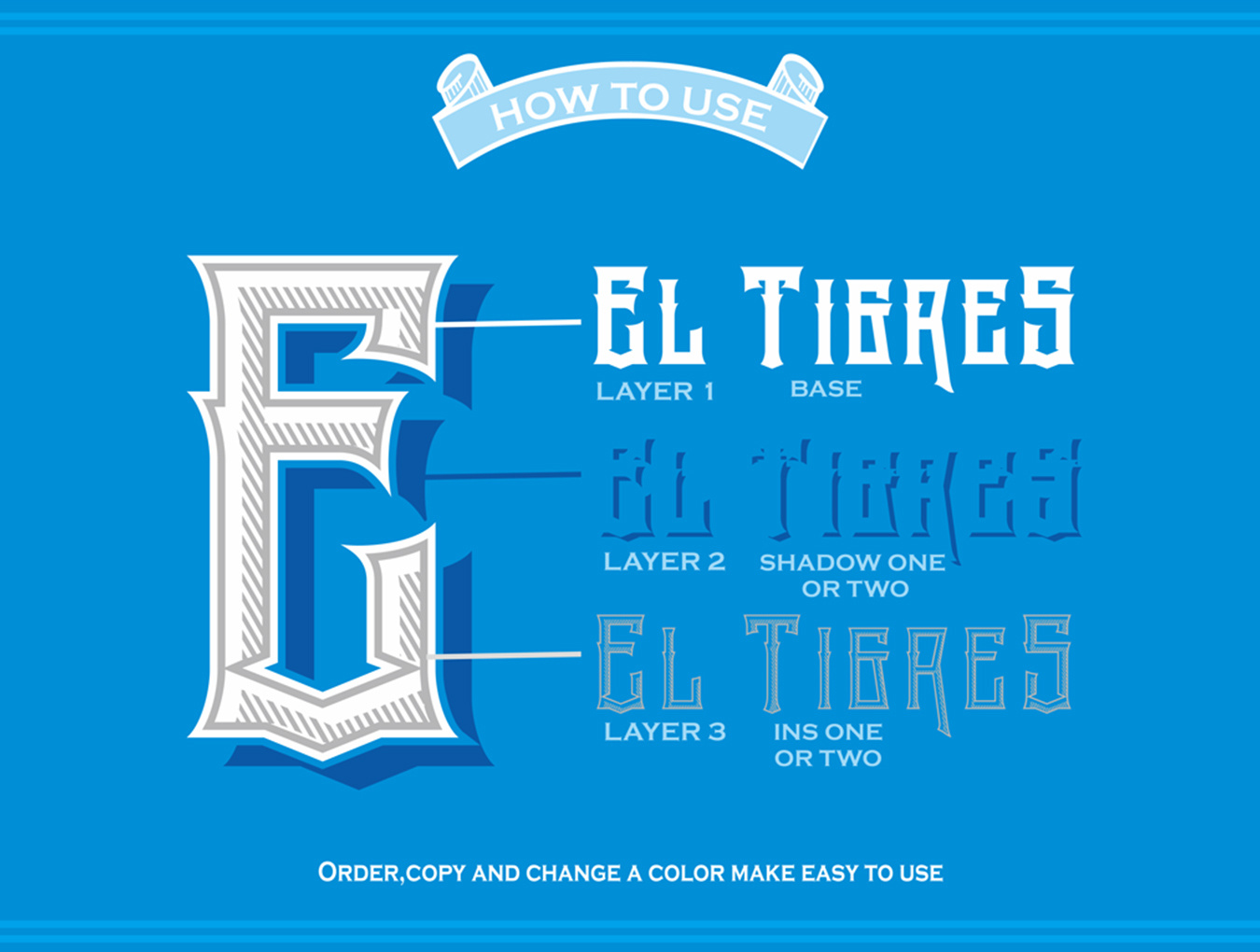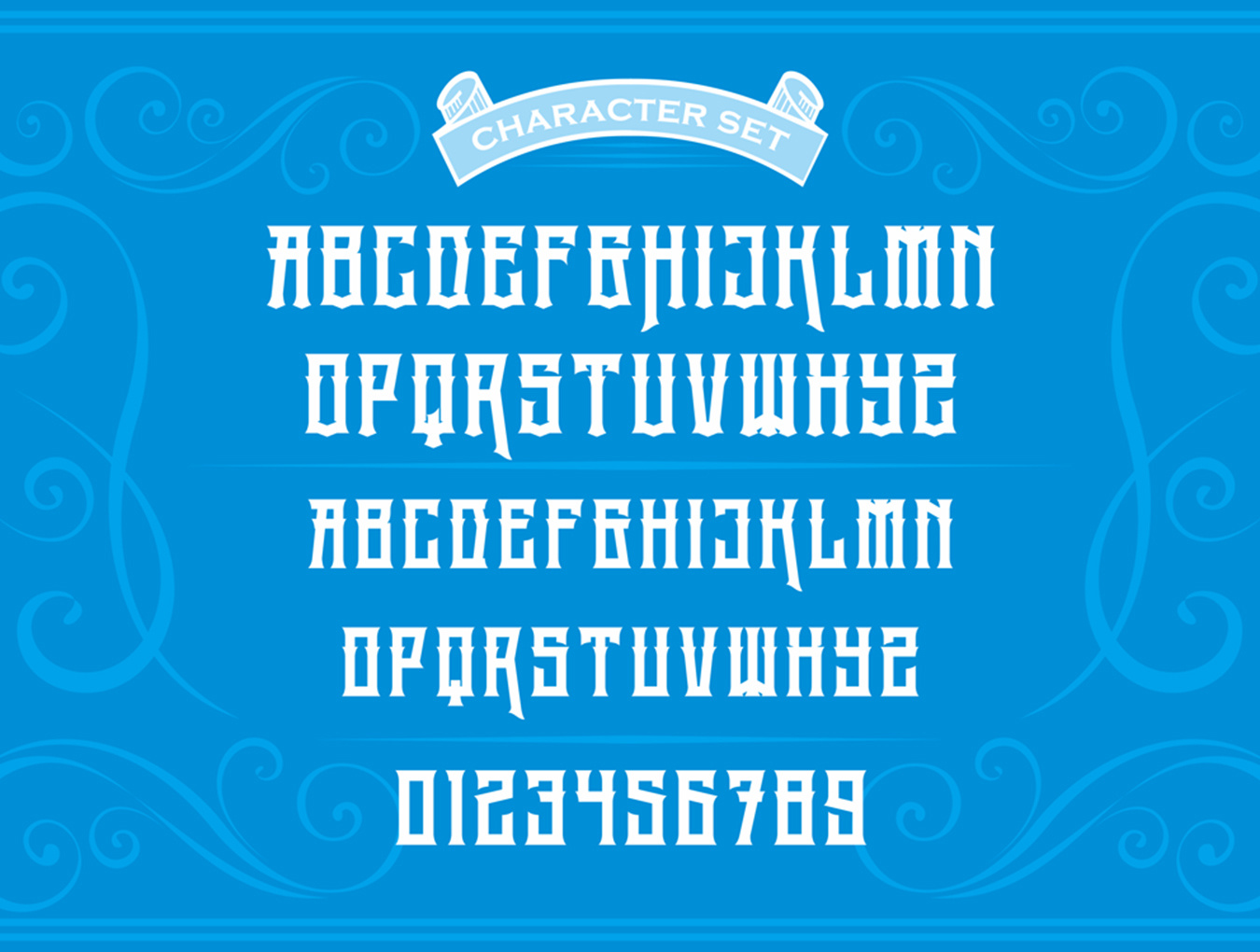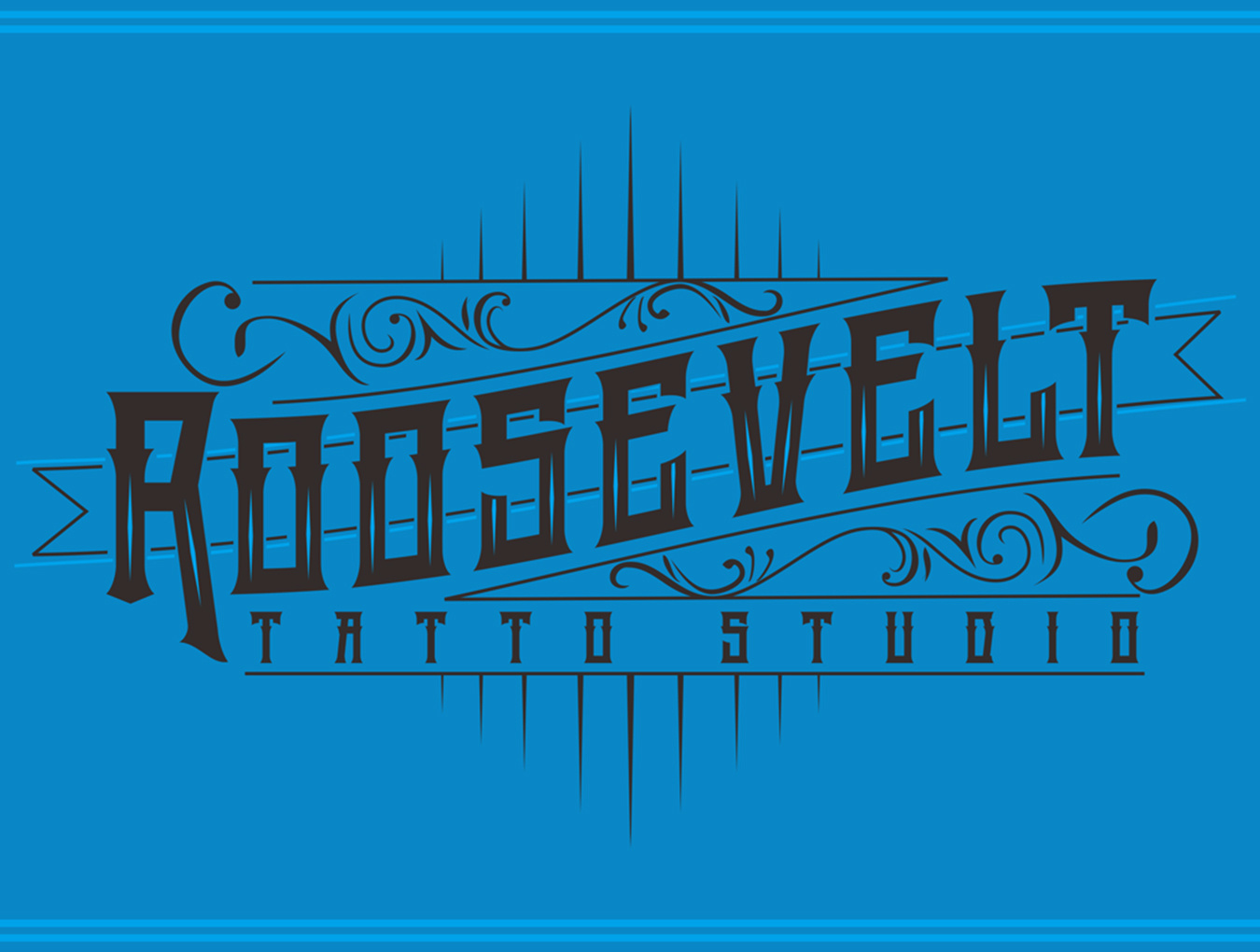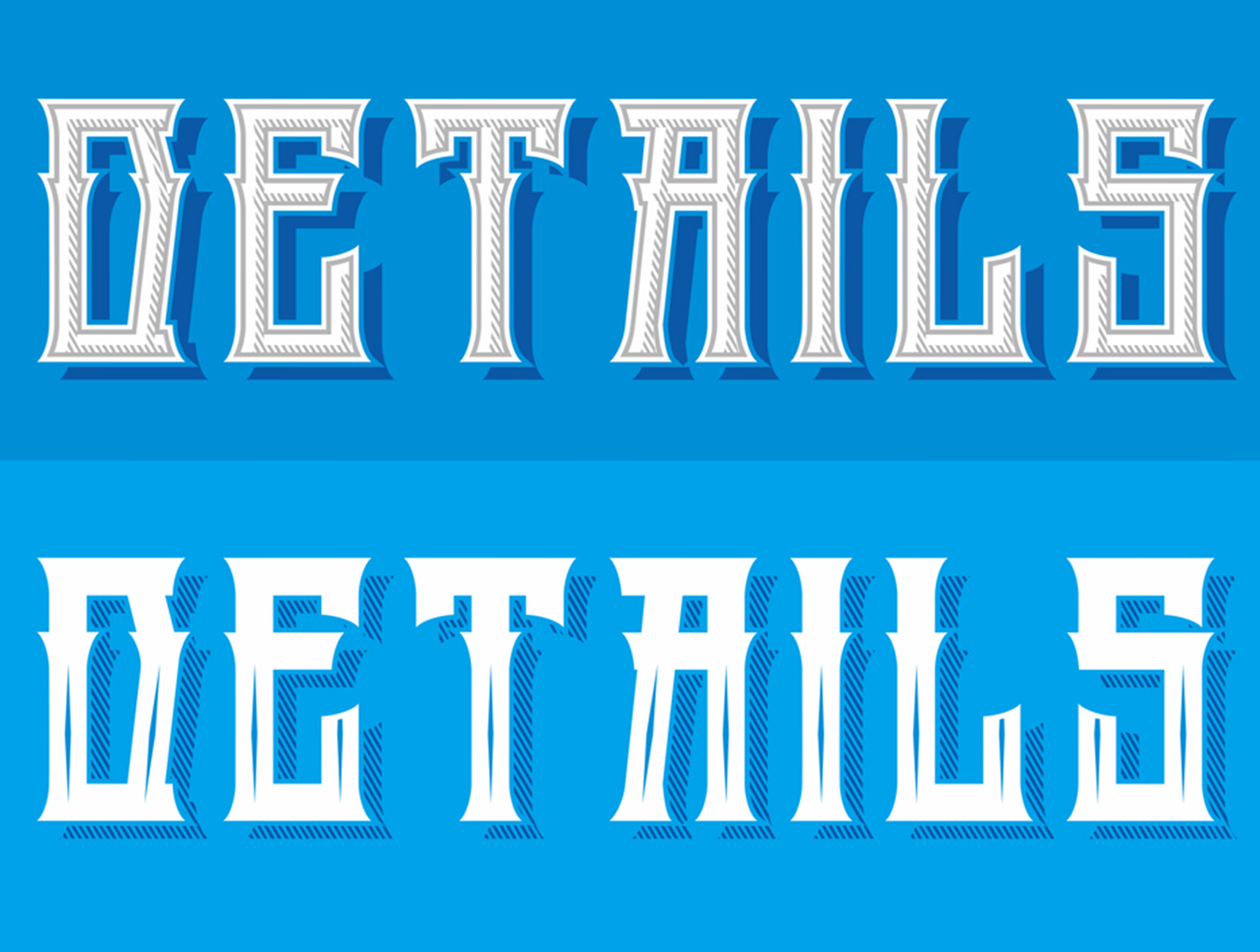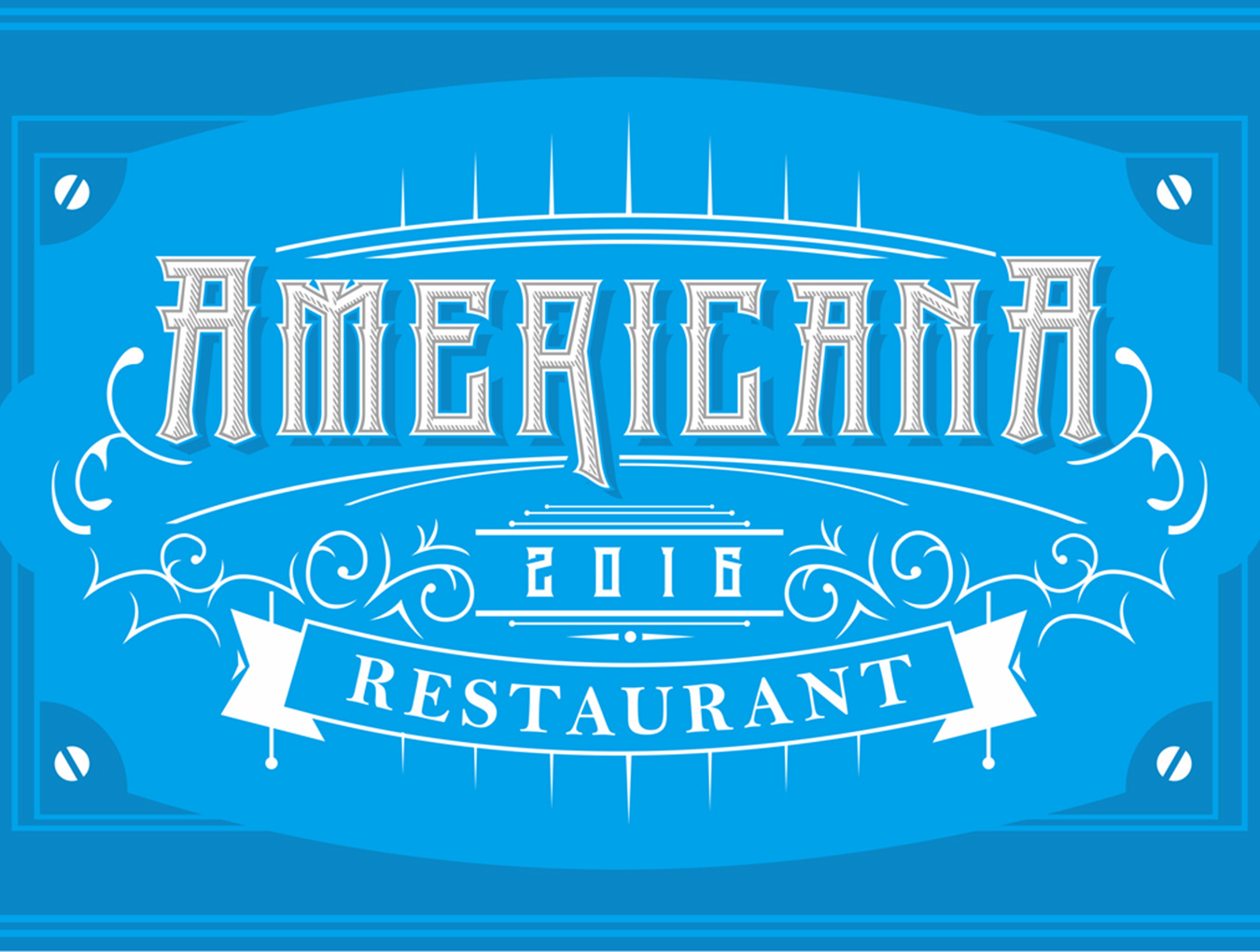
分层复古字体,El Tigres
A layered vintage typeface, El Tigres
El Tigres的灵感来自Ephemera设计和50年代60年代和70年代的经典旧复古设计。这种字体有OTF格式,有5层系列; El trigres,Ins one,Ins two,Shadow one&Shadow two。使用不同组合的这些图层可以获得各种字体样式。这种字体非常适合信头,标题,海报和标识。